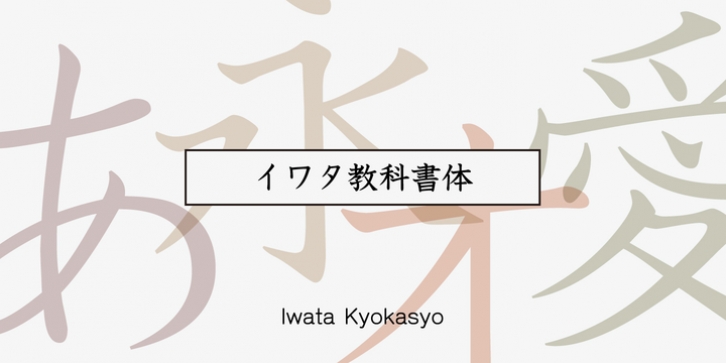
Iwata Kyokasyo Std was published by IWATA. Iwata Kyokasyo Std contains 4 styles and family package options.
å…童教育ã®ãŸã‚ã«ãƒˆãƒ¡ã€ãƒãƒã€ãƒãƒ©ã‚¤ã€ç†é †ã‚„画数を明確ã«ã—ãŸæ›¸ä½“ã§ã™ã€‚
教育用書ç±ã ã‘ã§ãªãã€æ§˜ã€…ãªæ›¸ç±ã«ã‚‚ã”使用ã„ãŸã ã‘ã¾ã™ã€‚